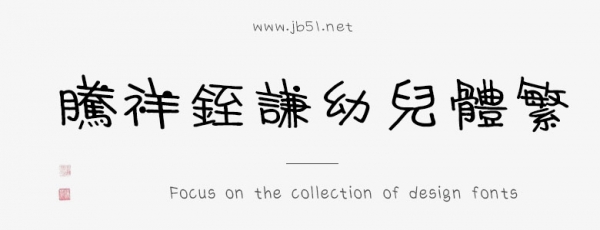
騰祥铚謙幼兒體繁是一款不錯(cuò)的藝術(shù)字體,由騰祥字庫出品,整幅字體風(fēng)格統(tǒng)一、行文規(guī)整,粗看似幼兒寫字歪歪斜斜,仔細(xì)看整個(gè)版面卻個(gè)性鮮明、極具功力,適合應(yīng)用于藝術(shù)設(shè)計(jì)、平面宣傳設(shè)計(jì)、網(wǎng)頁設(shè)計(jì),書法字帖等領(lǐng)域,需要的朋友可以前來本站下載。
此款字體是作者高铚謙先生撰寫的書法體字庫,整幅字體風(fēng)格統(tǒng)一、行文規(guī)整,粗看似幼兒寫字歪歪斜斜,仔細(xì)看整個(gè)版面卻個(gè)性鮮明、極具功力。字里行間充滿童真稚趣,彰顯活潑靈動(dòng)的個(gè)性。本作品可用于出版印刷、廣告設(shè)計(jì)、網(wǎng)頁設(shè)計(jì)、包裝設(shè)計(jì)、屏幕顯示。